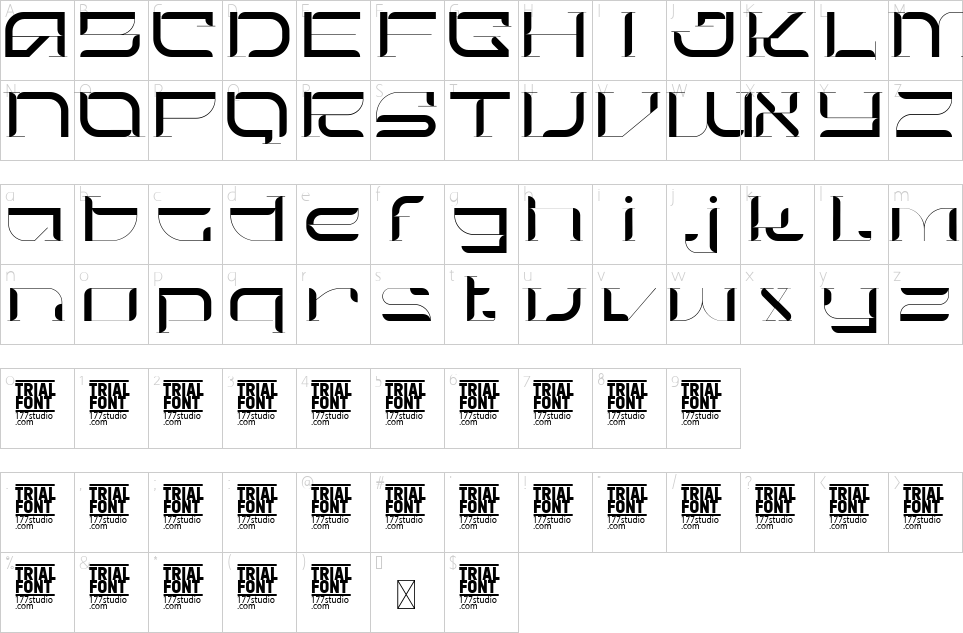
Digital Divide Font
Descubra a Digital Divide Font, uma opção gratuita que combina elegância com simplicidade para seus projetos digitais. Desenvolvida pelo 177studio.com, essa fonte já foi baixada por 234 usuários. A Digital Divide é ideal para quem busca um equilíbrio perfeito entre design moderno e facilidade de uso. Com sua arquitetura clean e versátil, a fonte Digital Divide combina bem com diversos estilos gráficos. Seja você um designer ou um amante da tecnologia, esta é uma excelente escolha para adicionar ao seu portfólio. Baixe gratuitamente a Digital Divide Font e experimente-a em seus próximos projetos digitais.